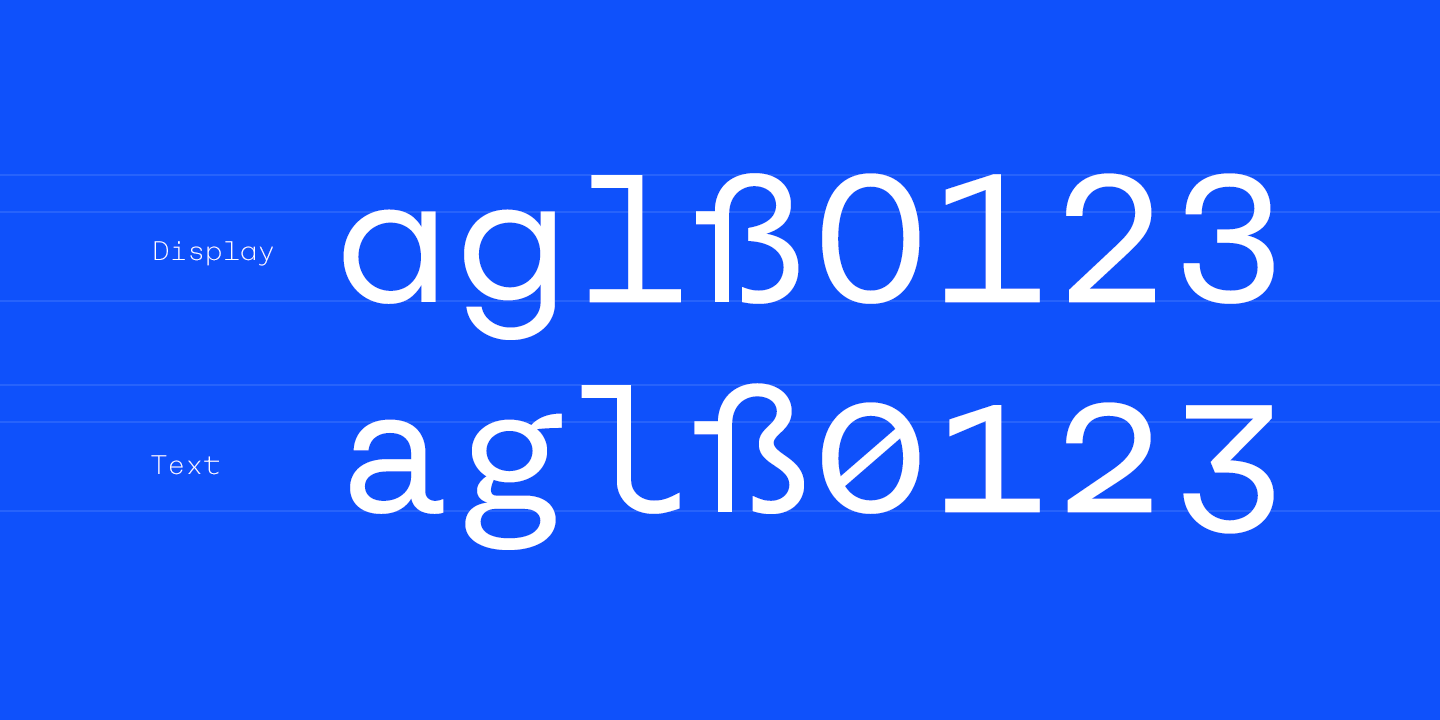
Geometrische Grotesk MONO
ich suche nach einer streng geometrischen Grotesk in Mono. Leider habe ich bisher weder bei den bekannten noch bei den kleinen Foundries etwas gefunden.
Die Schrift sollte unbedingt ein eingeschossiges a und g haben. Die Bögen müssen sehr hart in die Stämme einkaufen.
es soll ein add on für eine Haus Schrift sein. Den Auftraggeber kann ich leider nicht nennen.
Die space kommt nicht in frage. Da gibt es zu viele Details. Bei meiner bisherigen Recherche fand ich die Rational am besten, jedoch ohne das eingeschossige a soweit ich das sehen kann. Die Monosten ist ein super Hinweis und würde gar noch besser passen, ist jedoch durch die Rundungen nicht brauchbar.
Hey mein Fehler ich sehe die Rational Display hat ja sogar die eingeschossigen Zeichen! Danke!
Ich denke die Basis Grotesk Mono im styleset 1 wird wohl das Rennen machen. Da sind die Charakteristiken am besten in eine mono übertragen. Die Rational hat ein seltsam streifiges Schriftbild durch die sehr langen serifen.
Die hat aber doch kein einstöckiges a …?
Edit: Ah, doch, im SS01 hat sie es. Ist halt immer schwierig, wenn man sich alles zusammensuchen muss, weil links oder Bilder fehlen … ;-)